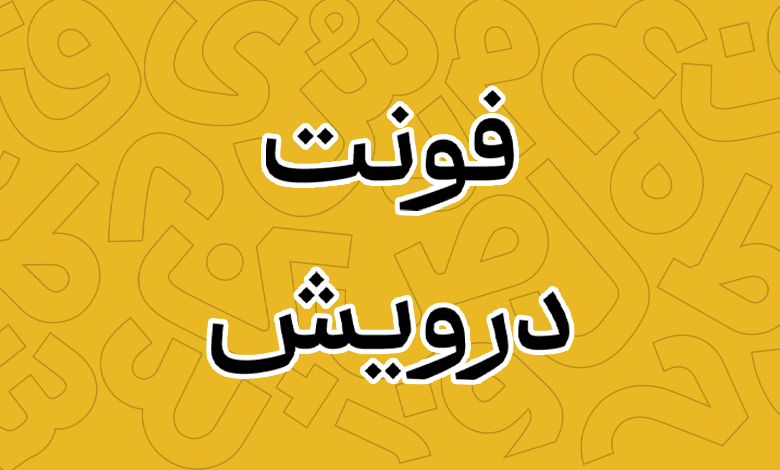
فونت درویش (Darvish)
فونت درویش (به انگلیسی: Darvish) با ترکیبی خلاقانه از خطوط ریحان و نسخ طراحی شده که هدف اصلی آن ارتقای خوانایی و افزایش جذابیت بصری در تایپوگرافی فارسی است. کشیدگی و بلندی خطوط ریحان در این فونت کوتاه‌تر شده‌اند تا وضوح بهتری به متن بدهند، همچنین حروف نسبت به سبک نسخ با عرض بیشتری طراحی شده‌اند. فونت درویش رایگان نیست و جهت استفاده می‌توانید آن را در ۳ بسته نرم‌افزاری مختلف خریداری کنید.
فونت «درویش» توسط طراح و تایپ‌فیس خوش‌ذوق؛ رضا بهلول طراحی شده است که با دقت فراوان در جزئیات، خوانایی و زیبایی بصری این فونت را خلق کرده است. این اثر منحصر به فرد، موفق به کسب جایزه معتبر تایپوگرافی از Type Directors Club (TDC) شده است.
در ادامه این نوشته به نقد و بررسی فونت درویش خواهیم پرداخت که در قالب ۱۰ وزن و با پشتیبانی از سه سبک جهت استفاده عموم عرضه شده است که در مجموع از نسخه وریبل برای استفاده بهتر در محیط وب‌فونت در دسترس است.
این ویژگی‌ها در کنار توازن بصری و خوانایی بالای فونت، باعث شده‌اند که فونت درویش توجه علاقه‌مندان و حرفه‌ای‌های طراحی را به خود جلب کند.
سبک طراحی و وزن فونت درویش
فونت درویش از ۱۰ وزن متنوع نازک و سبک تا سنگین، ضخیم و خیلی ضخیم را شامل می‌شود، که به کاربران امکان می‌دهد متناسب با نیاز پروژه خود از ضخامت‌های مختلف استفاده کنند. تنوع وزنی فونت درویش، آن را برای استفاده در عناوین، متون طولانی و حتی پروژه‌های چاپی و دیجیتال به گزینه‌ای مناسب تبدیل کرده است. ساختاری که این فونت دارد همچنین آن را به گزینه مناسبی برای استفاده به عنوان فونت رابط کاربری بدل کرده است.
فونت درویش دارای سه سبک متفاوت است:
• سبک معمولی (Normal): دارای ۸ وزن
• سبک گسترش‌یافته (Expanded): دارای ۶ وزن.
• سبک فشرده (Condensed): دارای ۱۰ وزن.
در حالی که سبک معمولی، ظاهر استاندارد و منسجم‌تری دارد و برای متون بلند و استاندارد به‌کار می‌رود، سبک گسترش‌یافته با عرض بیشتر خود در حروف، برای مواقعی که به طراحی مدرن‌تر یا تاکید بیشتر نیاز باشد، کاربرد دارد که از جمله کارکردهای آن می‌توان در فضاهای تبلیغاتی اشاره کرد. سبک فشرده نیز در نسخه دوم به‌منظور ایجاد حالتی میانه به این فونت افزوده شد.
این تفاوت در سبک‌ها، انعطاف بیشتری به طراحان می‌دهد تا به راحتی از فونت درویش در شرایط مختلف استفاده کنند و بتوانند به طور همزمان زیبایی و خوانایی را حفظ کنند.
به طور کلی، فونت درویش با الهام از سبک طراحی نسخ و ریحان، همواره زیبایی بصری را با خوانایی بالا همراه کرده است و از این رو، یک گزینه مناسب برای استفاده در پروژه‌های حرفه‌ای تایپوگرافی فارسی است.
فونت رایگان درویش با پشتیبانی از چهار زبان فارسی، عربی، کردی و انگلیسی، انعطاف و کاربری بالایی برای کاربری چندزبانه ارائه می‌دهد. در پروژه‌هایی با محتوای چندزبانه هماهنگی و انسجام بیشتری را در اختیار قرار خواهد داد. تفاوت‌های گلیفی که در این فونت برای زبان‌های مختلف وجود دارد، آن را از بسیاری از فونت‌های معمولی متمایز کرده است و همین دقت در طراحی گلیف‌ها، به خوانایی و جلوه بصری فونت کمک زیادی کرده است.
گلیف‌های عددی و حروف فارسی و عربی در فونت درویش به گونه‌ای طراحی شده‌اند که بتوانند ظاهری هماهنگ و خوانا ارائه دهند؛ ولی با دقت به تفاوت‌های جزئی میان سبک تایپ فارسی و عربی. به عنوان مثال، اعداد در فونت درویش با ظرافت خاصی طراحی شده‌اند که هم برای زبان فارسی و هم برای عربی قابل استفاده هستند، ولی در عین حال به تفاوت‌های ظاهری هر دو زبان احترام می‌گذارد که از جمله آنها می‌توان به تفاوت ظاهری اعداد «۰۴۵۶» عربی نسبت به اعداد «۴۵۶» فارسی اشاره کرد.
گلیف‌های تزئینی کردی یکی دیگر از ویژگی‌های برجسته این فونت است که آن را برای استفاده در پروژه‌های کردی‌زبان منحصربه‌فرد می‌کند. این گلیف‌های تزئینی به متن نمایی خاص و جذاب می‌بخشند. طراحان می‌توانند با استفاده از این گلیف‌ها، جلوه‌ای بومی به پروژه‌های خود بدهند؛ به‌ویژه زمانی که نیاز به تمایز و اصالت بیشتر دارند.
برای زبان عربی، فونت درویش از اعراب‌گذاری استاندارد پشتیبانی می‌کند که به بهبود خوانایی و وضوح بیشتر کلمات کمک خواهد کرد. این گلیف‌های اعراب‌گذاری، به ویژه در متون مذهبی و ادبی عربی که نیاز به دقت بالا در نمایش صحیح حرکات و آواها دارند، به کار می‌آیند و از نظر زیبایی‌شناختی نیز به متن نمایی منظم و یکدست می‌دهند. از سوی دیگر با توجه به پشتیبانی از سبک اکسپند فونت، می‌تواند ظاهری نمایشی هم به حروف بدهد.
در نهایت، پشتیبانی از زبان انگلیسی در فونت درویش نیز با دقت در طراحی حروف و هماهنگی با سایر زبان‌ها صورت گرفته است. گلیف‌های انگلیسی به گونه‌ای طراحی شده‌اند که در کنار حروف فارسی و عربی، ظاهری منسجم و هماهنگ داشته باشند و در پروژه‌های چندزبانه، یکپارچگی بصری را به خوبی حفظ کنند.
امکان استفاده از ۵ سبک نقطه گذاری
در نسخه دوم فونت درویش این امکان فراهم شده تا بتوانید شکل نقطه‌گذاری حروف را در ۵ حالت مختلف مشابه تصویر زیر تایپ کنید.